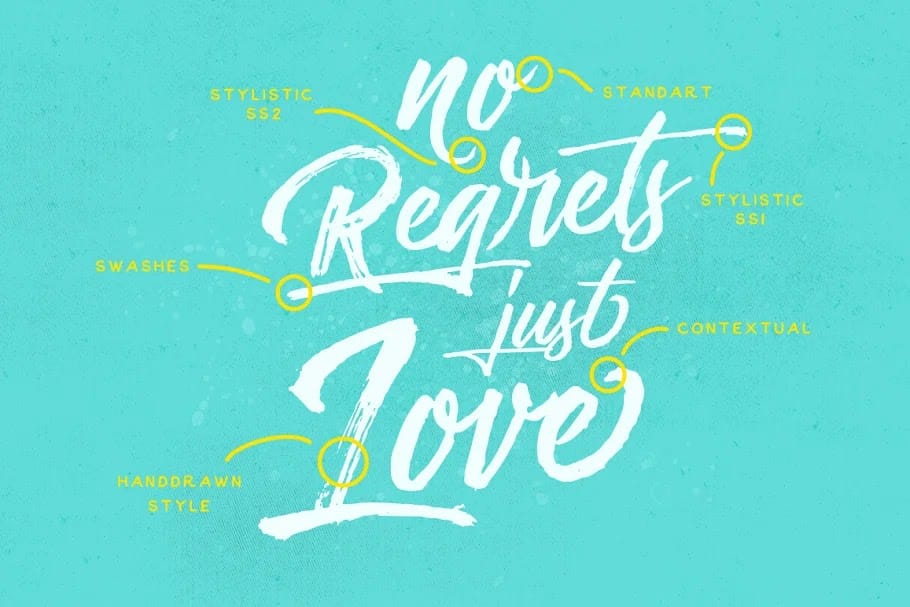
Messy Script là kiểu chữ vẽ tay được thiết kế để giúp bạn tạo ra thiết kế của chữ viết tay tuyệt đẹp. Messy Script đi kèm với các ký tự viết hoa và viết thường, dấu chấm câu, chữ số và các tính năng OpenType. Font chữ phù hợp rất nhiều thiết kế khác nhau như typo, quotes, poster…
Các lựa chọn thay thế cho các ký tự cũng có sẵn nhưng không nhiều, có thể truy cập qua Glyphs.